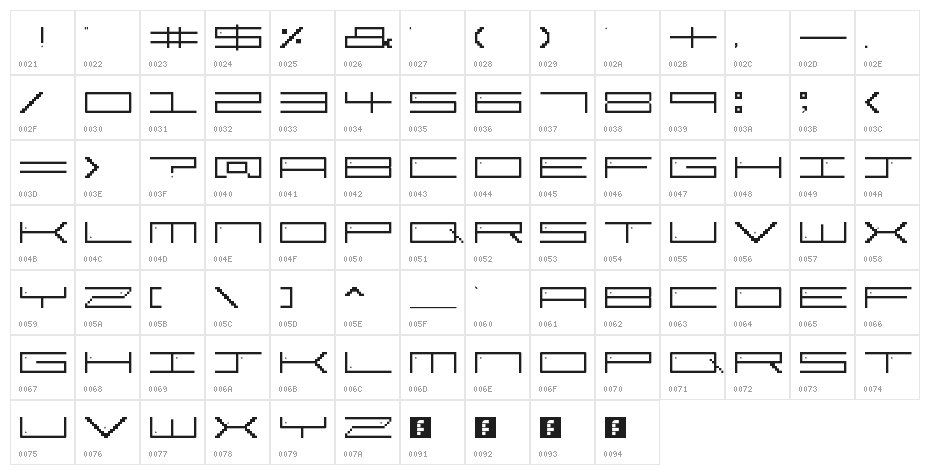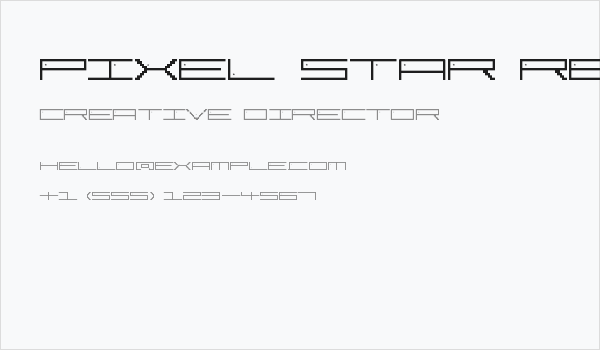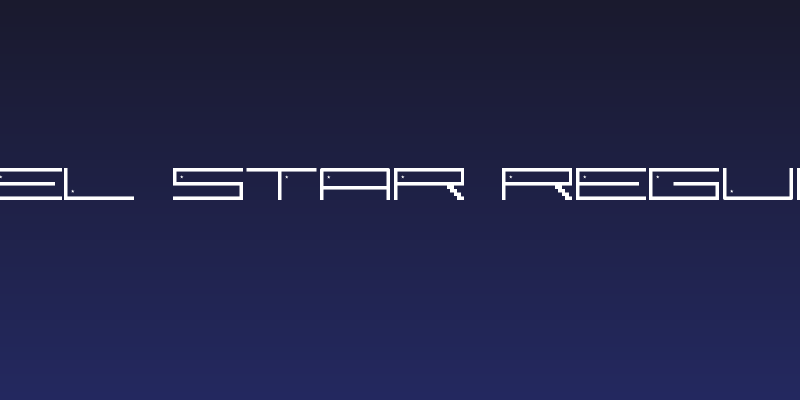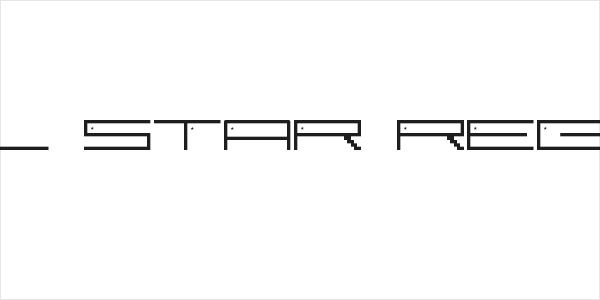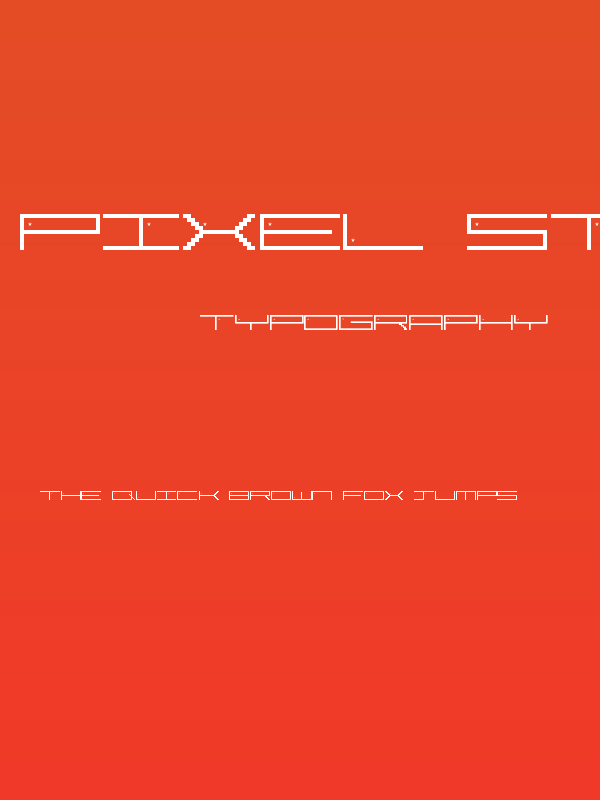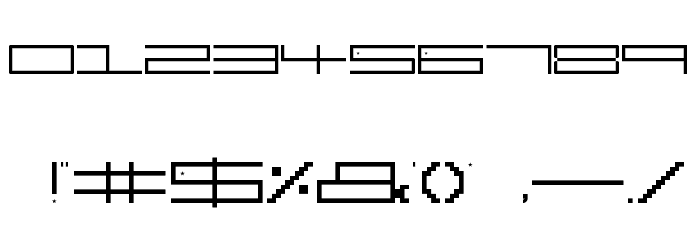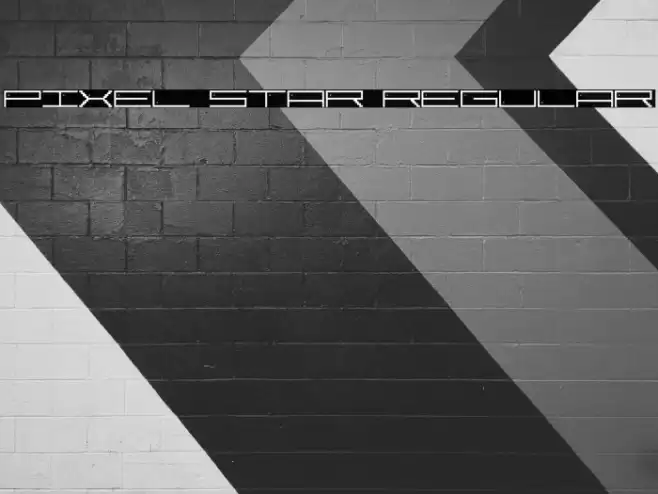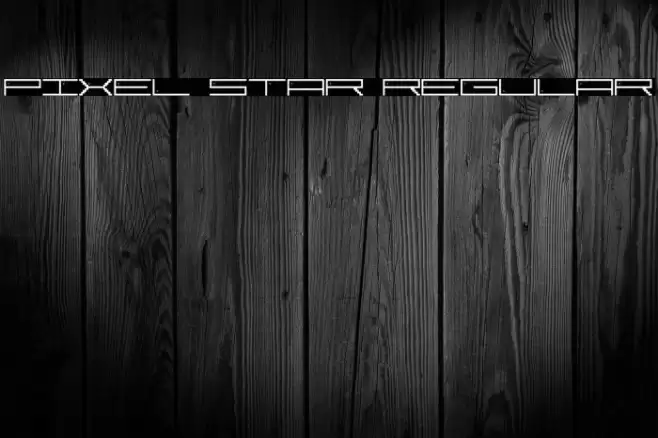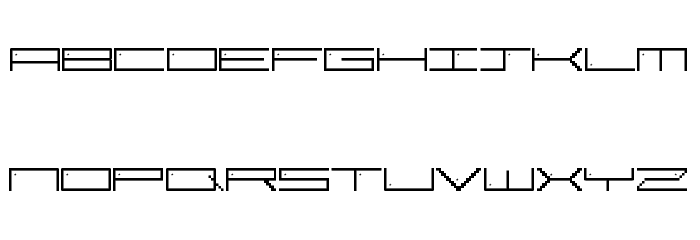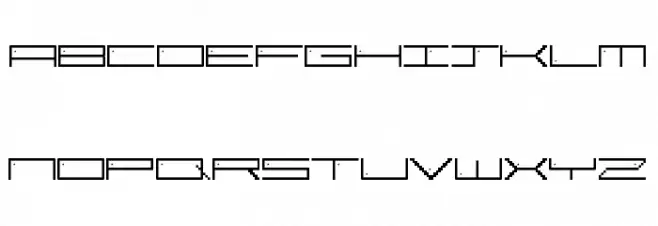
Pixel Star Regular Font
| Estilo geral | Retro, Digital |
| Projetos propostos | Ideal for video game design, tech-themed posters, digital art projects, or any creative work that seeks to evoke a sense of nostalgia for early computing. |